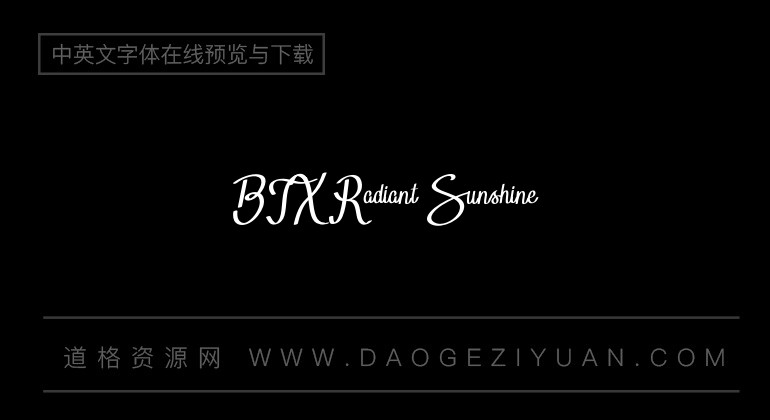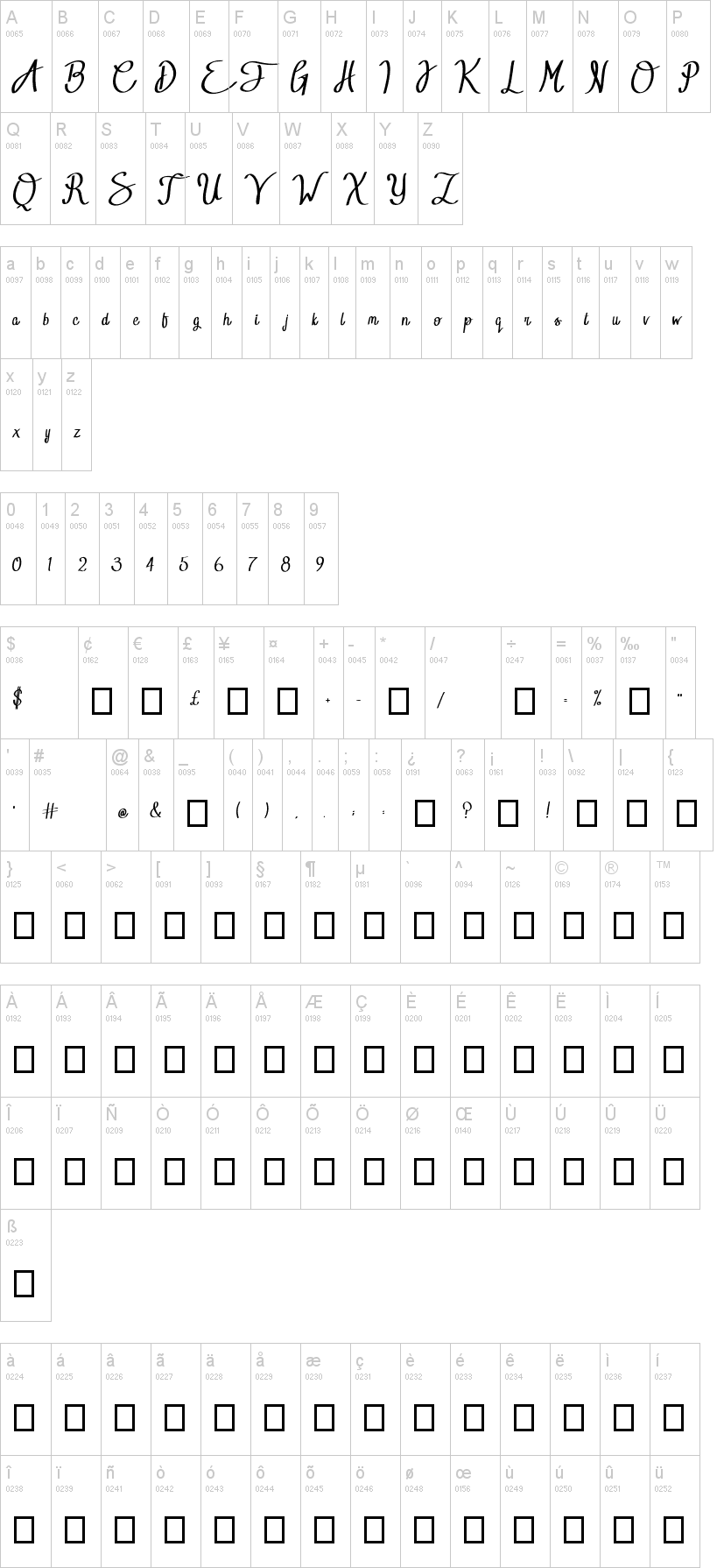
BTX Radiant Sunshine 字体是一款由 BTX Fonts 出品的手写体字体。它拥有温暖明亮的外观,带有一种活泼可爱的气息,非常适合用于制作卡通图案、儿童书籍封面等等。它的设计灵感来源于太阳,具有明亮的外观,而且拥有柔和的线条,可以让您的作品充满活力和温暖的感觉。内容介绍
BTX Radiant Sunshine是一款非常不错的手写艺术字体,具有很好的视觉感,适合于文化类的宣传设计、商业类品牌的广告和产品包装设计以及个性化文字排版等较多场景。